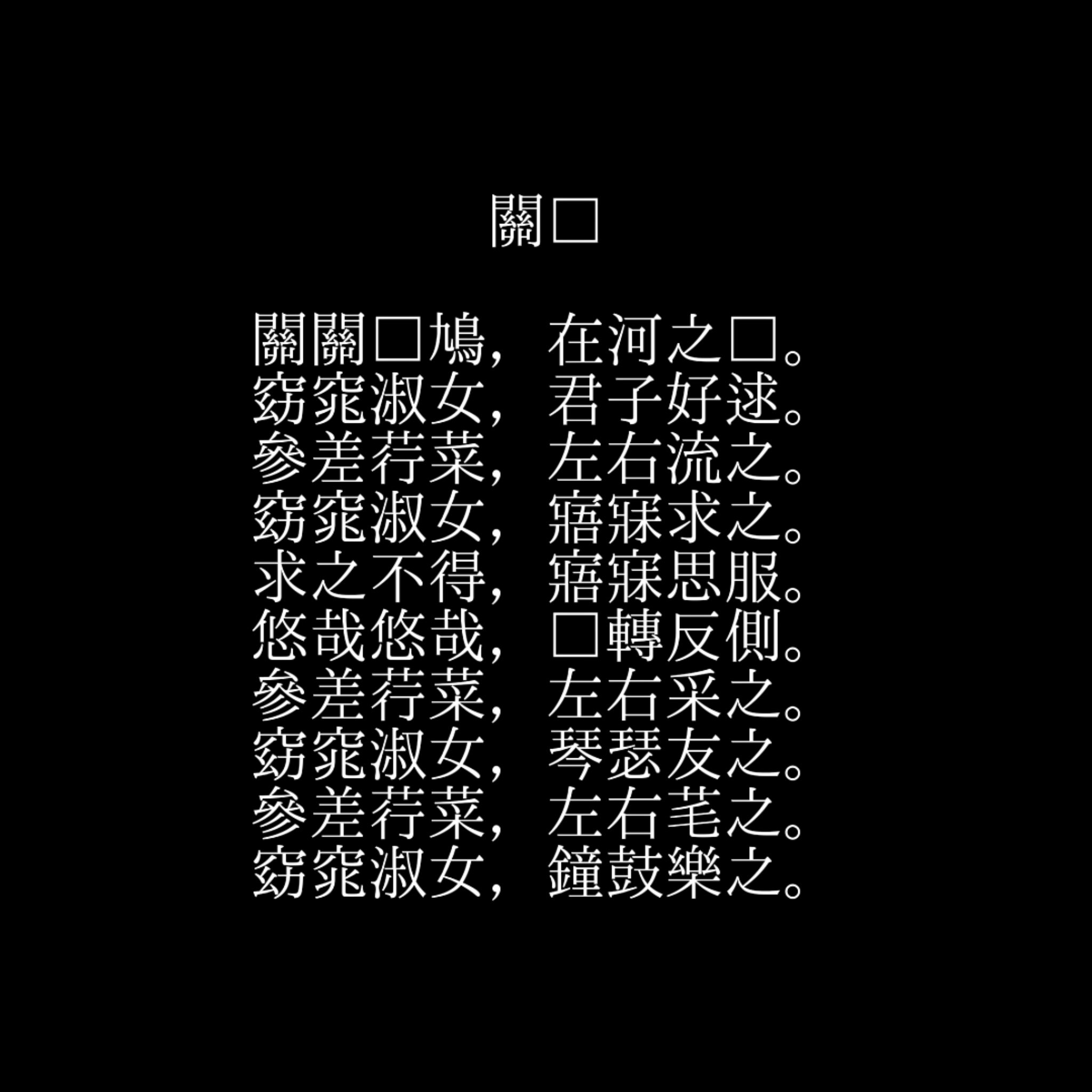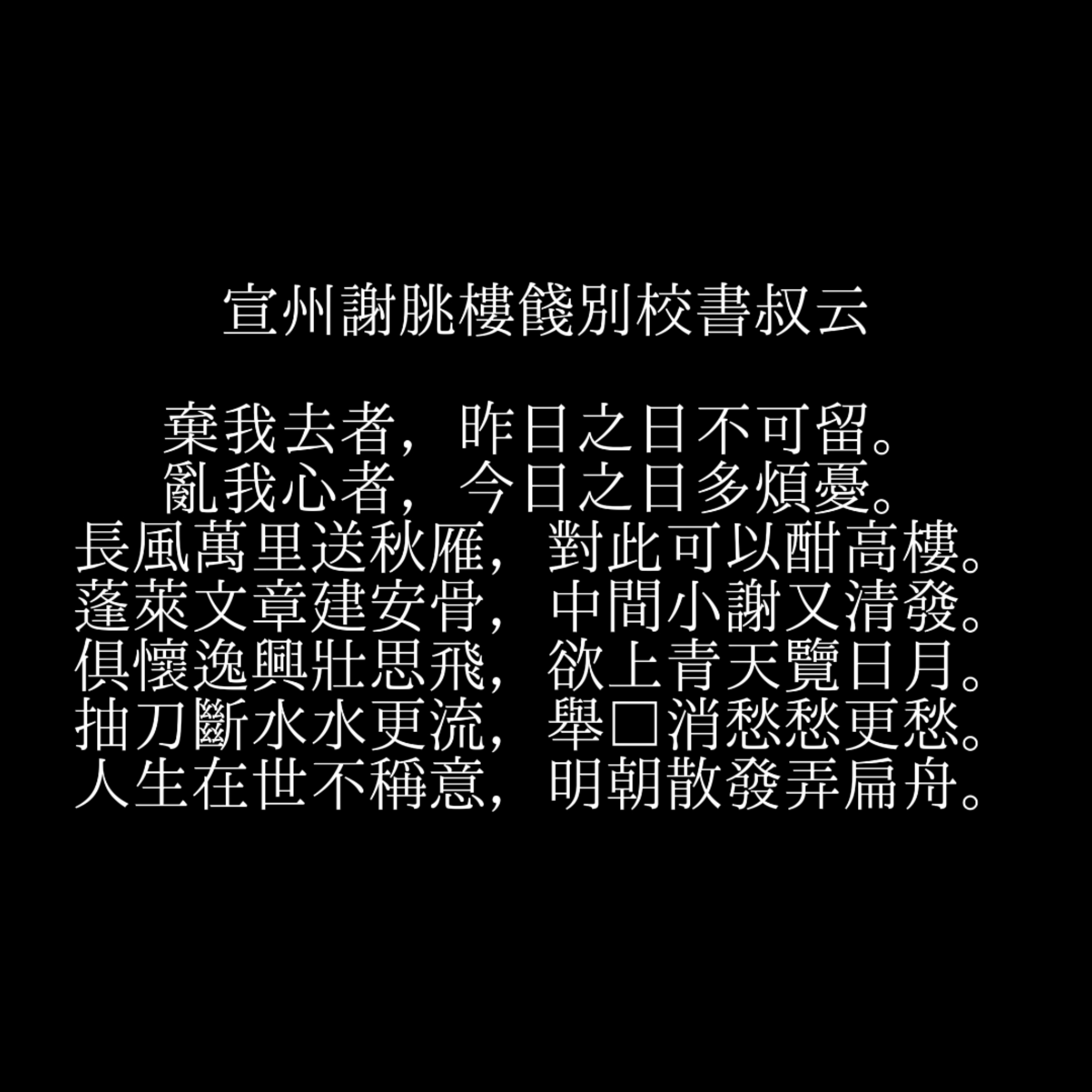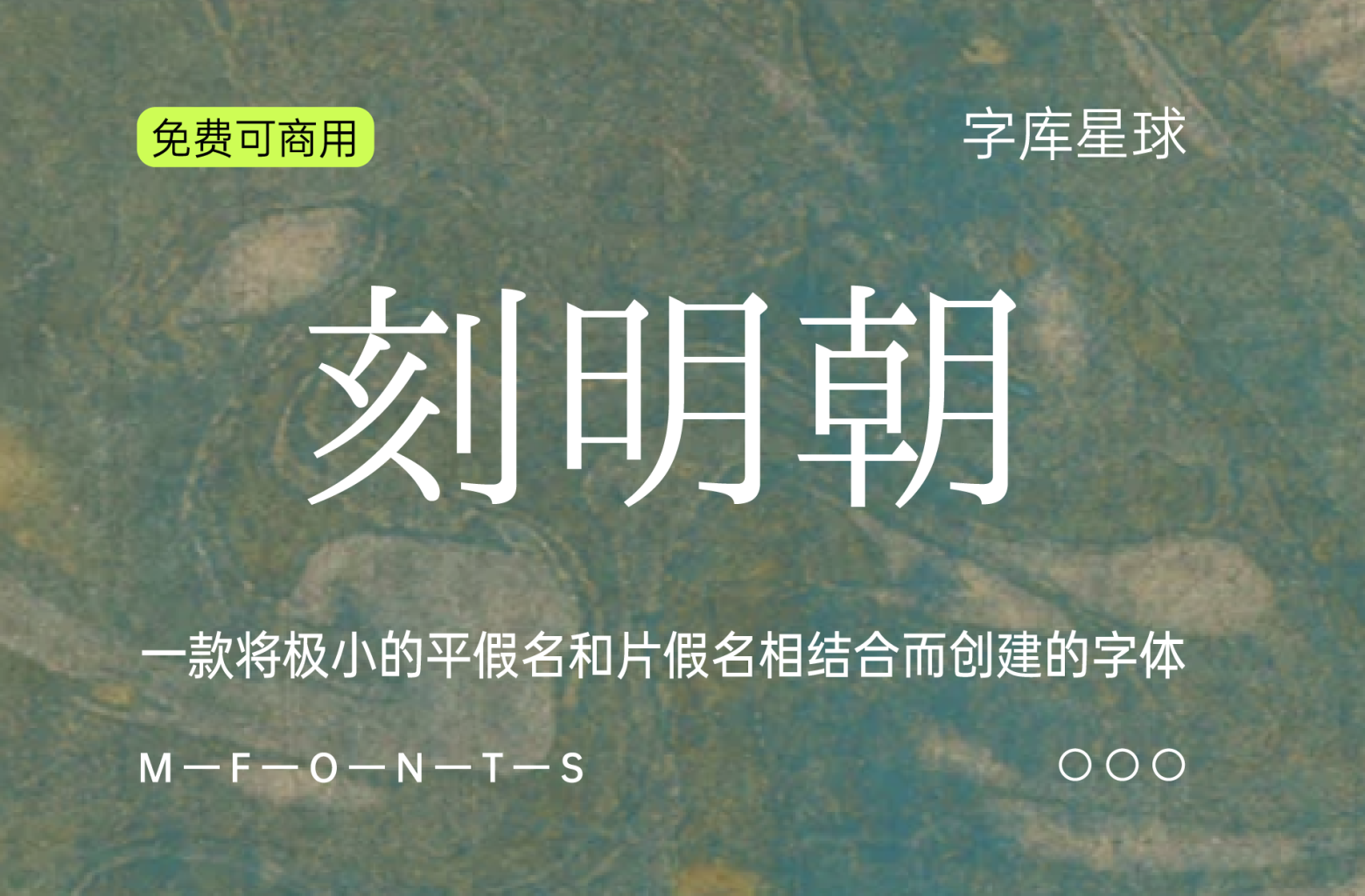
刻明朝是一种通过将极小的平假名和片假名与普通明朝汉字字体相结合而创建的字体。与平假名和片假名原本柔软自然的形状形成对比,其特点之一是人工和略带机械的“硬度”。至于假名字符,单杠像汉字一样笔直地延伸到侧面,并且具有相似的刻度。竖条也不同,装饰类似于字母的线条。它正是一种具有汉字字体和字母字体融合的假名字符的字体。
平假名和片假名具有独特的元素,但并不夸张,并以沉稳的设计完成。曲线流畅地改变粗细,给人一种优雅浪漫的印象。该设计与假名字符的原始骨架相去甚远,但它具有遵循每个字符的面部表情的礼貌骨架,因此不影响可读性。
文章标题:刻明朝